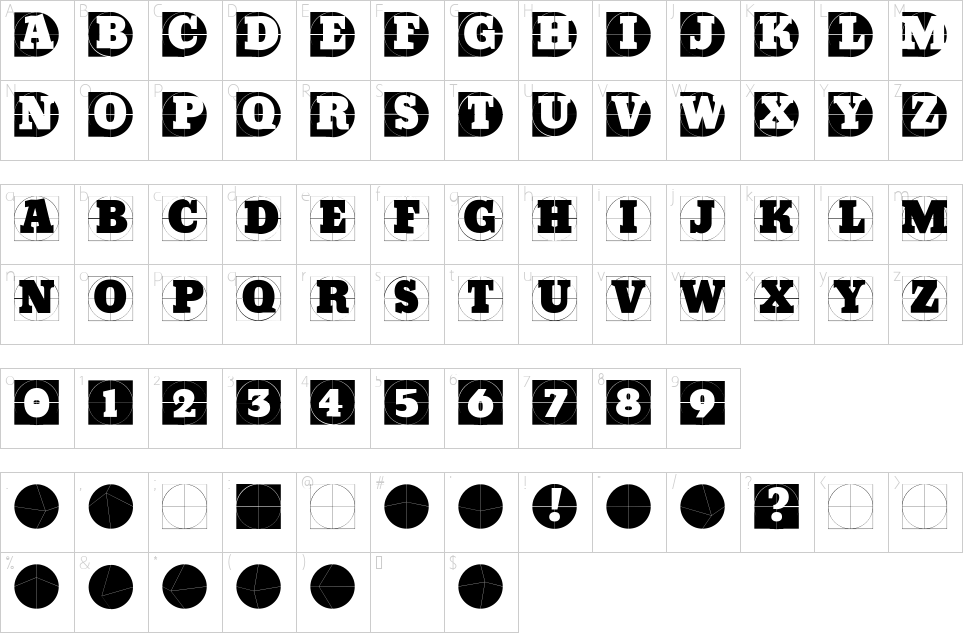
A Grid Concrete é uma fonte robusta e minimalista que se destaca entre as demais graças à sua rigidez geométrica e proporções equilibradas. Desenvolvida pelo designer Manfred Klein 函, essa fonte foi projetada com simplicidade, tornando-a uma escolha ótima para aplicações onde a clareza do texto é crucial. Seja em ambientes de escritório ou publicações digitais, a Grid Concrete oferece um equilíbrio entre funcionalidade e design limpo, permitindo que o texto seja fácil de ler em várias dimensões e tamanhos. A sua natureza sólida e direta contrasta perfeitamente com as abstratas gráficas contemporâneas, tornando-a uma opção ótima para designers buscarem equilíbrio e consistência no seu trabalho. Download gratuitamente a Grid Concrete font para Windows e Mac e descubra por si mesmo o potencial desta ferramenta de design. Esta fonte foi projetada para ser utilizada em qualquer aplicação que necessite de uma solução clara e confiável, criando um impacto visual sólido. É uma escolha inteligente tanto para designers digitais quanto para editoras digitais, fornecendo a consistência necessária para tornar um trabalho único em um ambiente digital altamente concorrido.